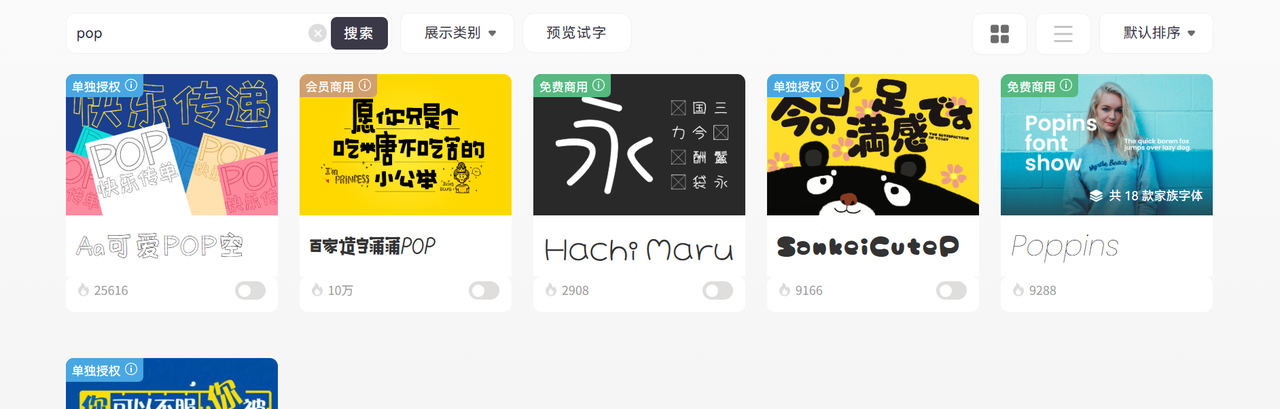
去年我帮朋友的奶茶店设计促销海报时,遇到了一个让人头疼的问题,想要那种活泼醒目的POP字体,但网上下载的字体要么不能商用,要么授权费贵得离谱。后来我花了不少时间,总结出了8个真正可以免费商用的POP字体下载网站。
字由平台中查找 POP 字体的方法
直接在搜索框中搜索
分类筛选
因为搜索是完全匹配的逻辑,所以搜出来的字体不是很多,你可以根据分类来进行筛选查找,比如你可以筛选免费商用的创意字体,这里面有非常丰富的 POP 字体供你选择
AI 生成
进入字体工具 - AI 字体界面
选择适合你的 POP 字体模板,就可以快速借助 AI 完成 POP 字体设计和下载
站酷系列字体在设计圈里很有名,比如站酷快乐体、站酷高端黑、站酷庆科黄油体等。这些字体都是由设计师团队精心设计,质量很高,风格多样,其中有几款特别适合做POP设计。